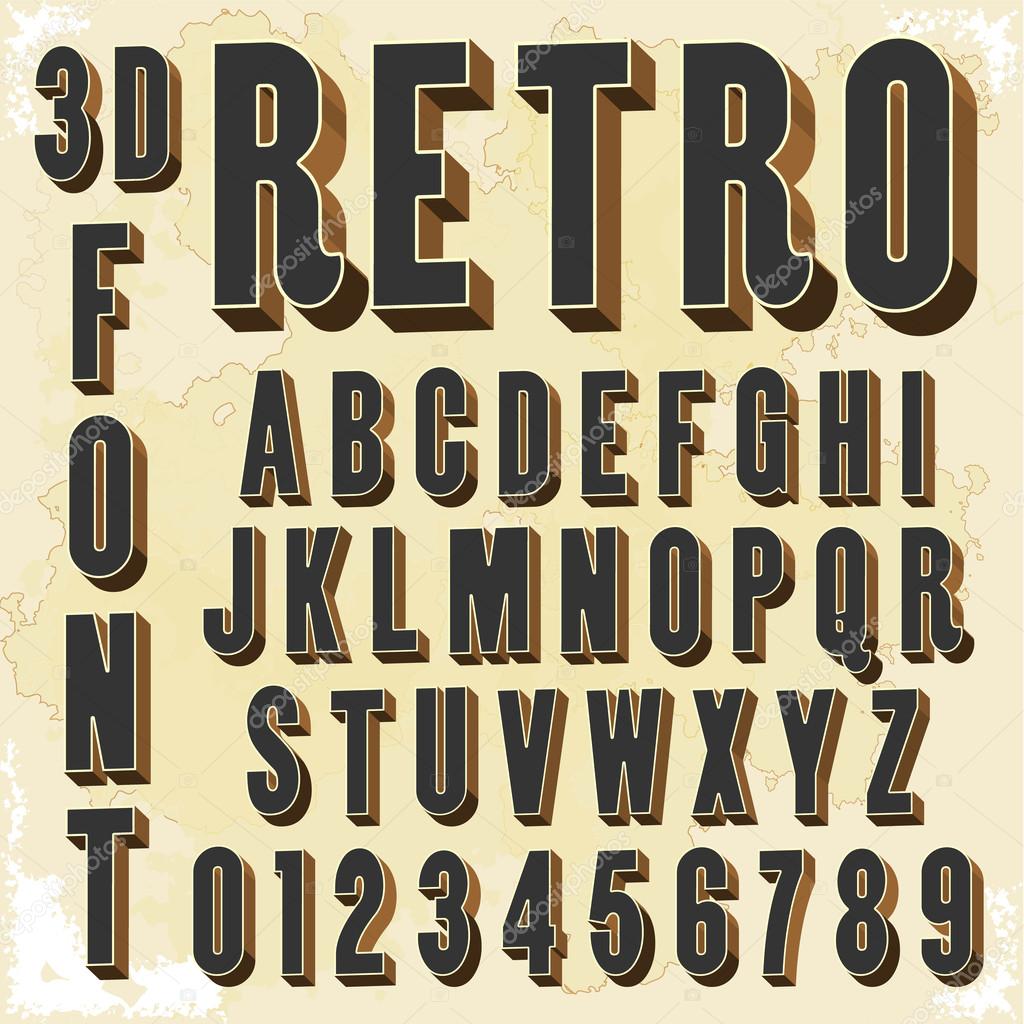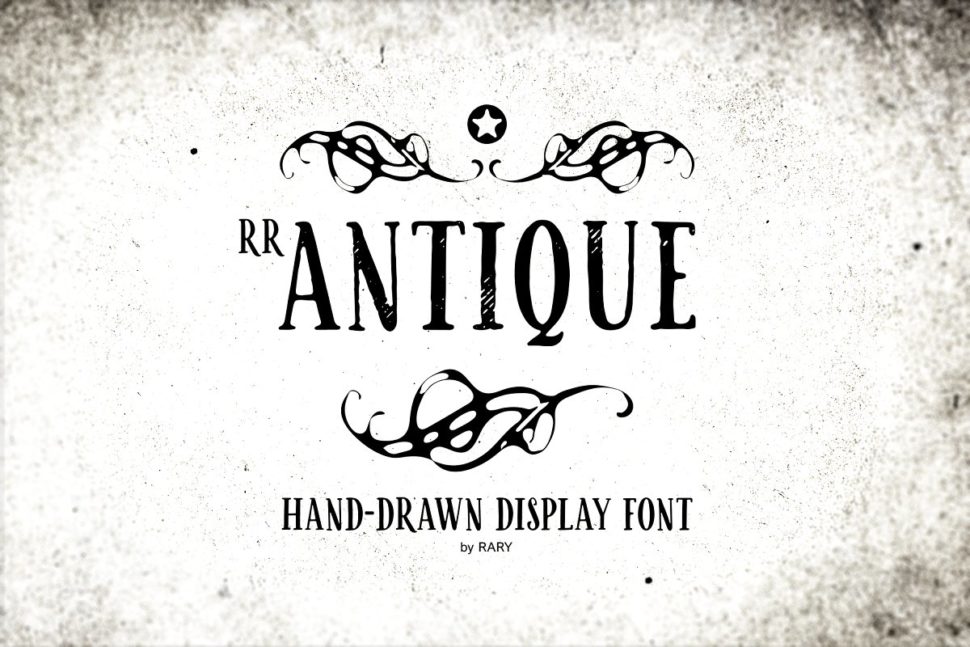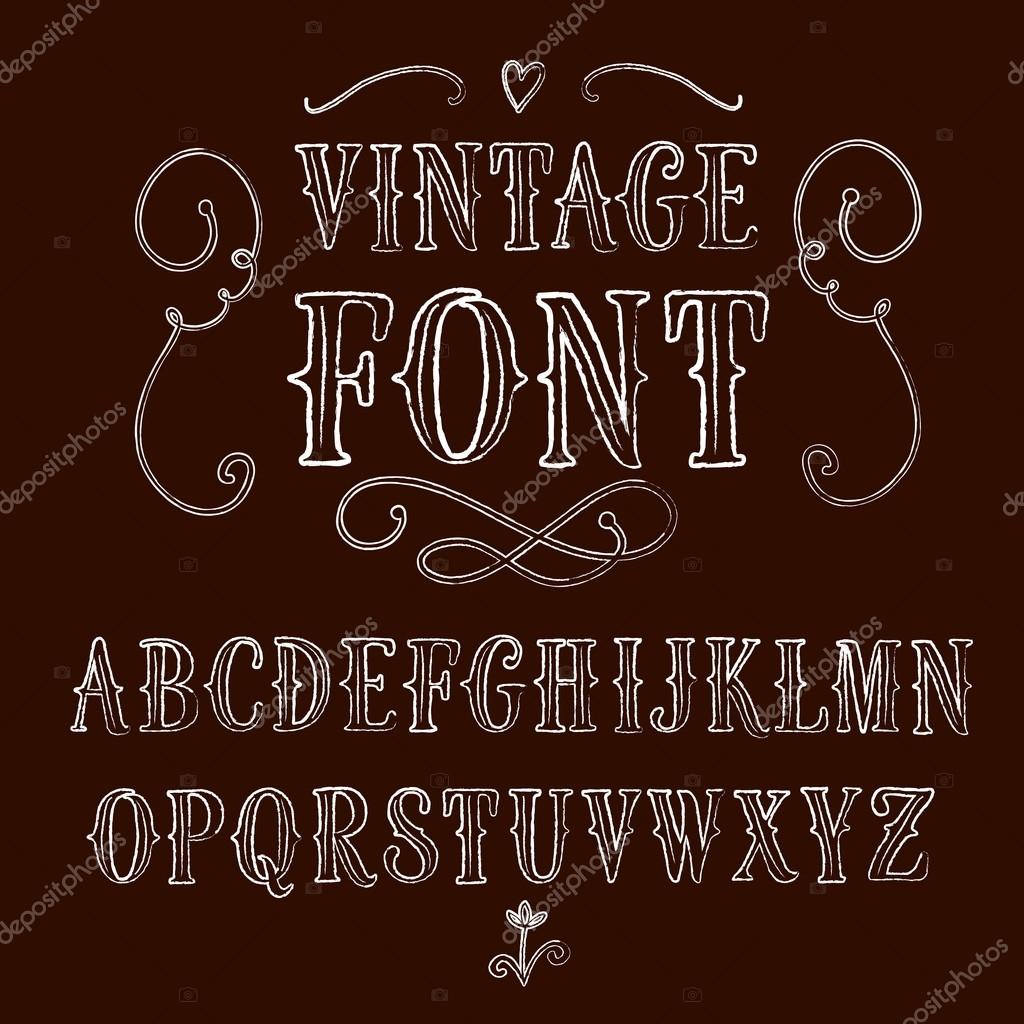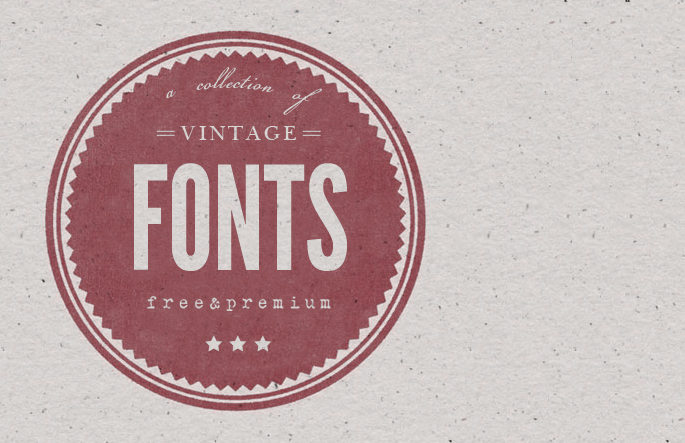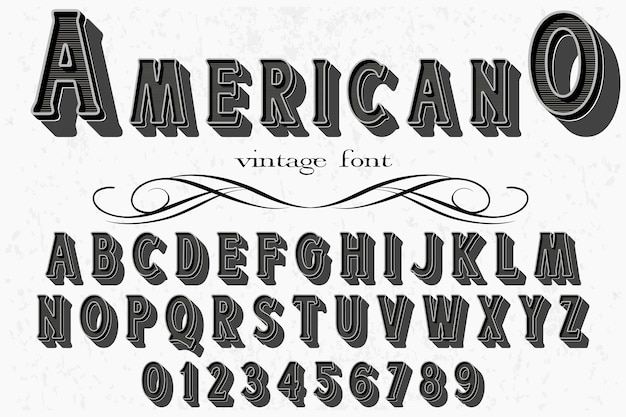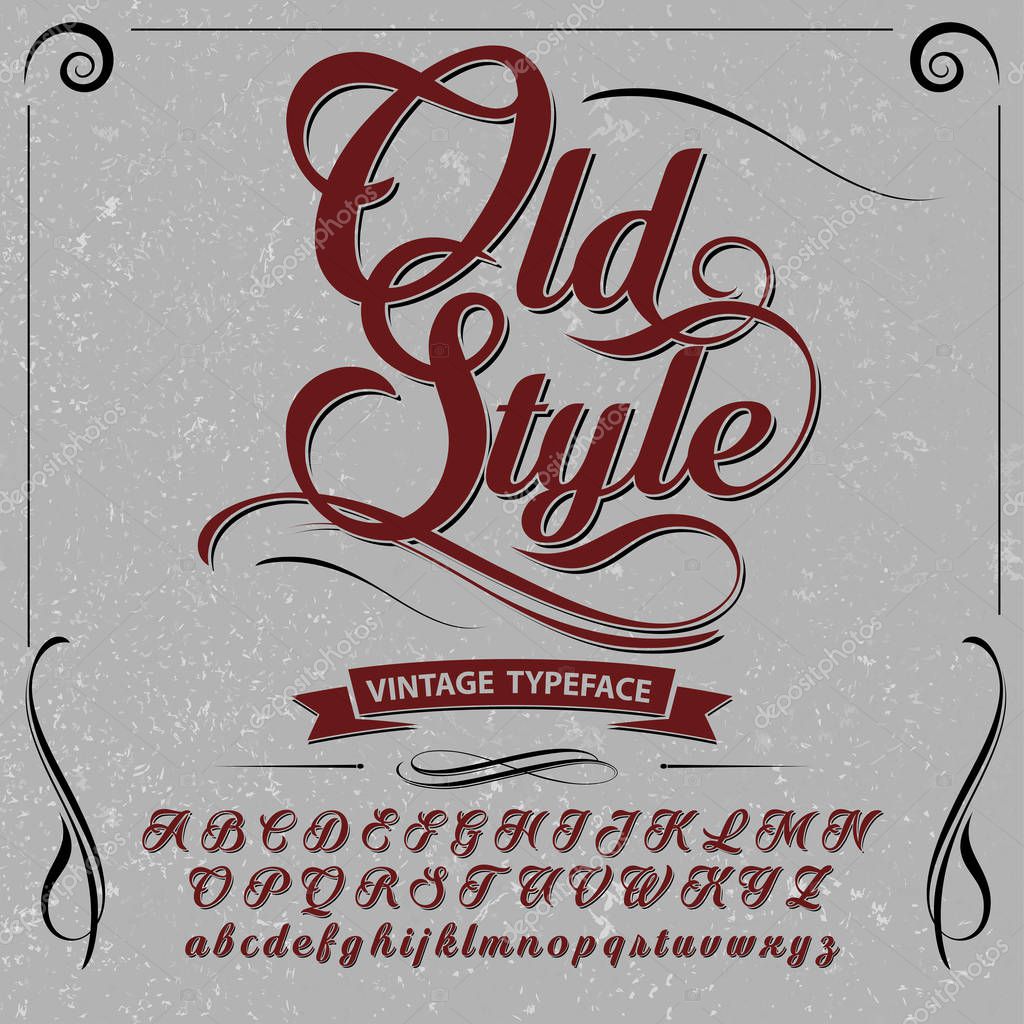
Взгляните на эти замечательные старинные шрифты. Они могут быть не новыми, но они все равно могут принести вам такое влияние, которого вы никогда не видели.
Есть одна веская причина, по которой старинные шрифты все еще используются сегодня. Они выдержали испытание временем и доказали, что могут продолжать добавлять уникальную привлекательность к дизайну, несмотря на то, что на рынке появляются более современные тенденции.
1. Caja
2. Cassannet Plus Regular
3. Bough Handdrawn Typeface
4. Bernier Type Family
5. Nickainley Monoline Script Font
6. Duwhoers Modern Brush Font
8. Refuge Handcrafted Font
9. Blnc Round
10. Draft Display
11. Kino 40 Typeface
12. Hobric Rough
13. Contact High
14. Ren free font
15. Arkana Script Vintage Font
16. Canyons Vintage Script
17. Rising Star Monoline Script
18. Zeyk Brush Typeface
19. Lauren Script Font
20. Awesawez Script
21. Diamor Script
22. Little Cutie
23. Sitka Brush
24. Logawa Script
25. Elrotex Brush Font
26. Something Wild Free Font
27. Arabella
28. Morracle Font
29.
Бесплатные винтажные и ретро шрифты
Дизайн в стиле ретро предназначен для отсылки в прошлое, и желательно, не меньше чем лет на 40-50. Такой дизайн передает особую атмосферу, придает проекту выдержанность хорошего коньяка и даже немного играет на нащей ностальгии. Для этого используют различные методы — например, элементы в винтажном стиле, ретро паттерны, текстуры, цветовые гаммы. Важное место здесь занимает типографика. Для свежей подборки мы нашли 17 самых атмосферных (и бесплатных!) ретро шрифтов, которые отражают настроение 1920—1960 годов прошлого века.
Matchbook
Bazar, Medium
Embossed Black
Ugly Qua
Hill House
Shrewsbury-Condensed Bold
Caslon
Seaside Resort
Fontleroy Brown
Fusty Saddle
Dirty Ames
Just Old Fashion
Goudy Bookletter 1911
Circus Ornate
BP Script
Rocket Script
Anagram
Copper
Названия фильмов 80-х и начала 90-х годов вдохновляют дизайн шрифта Copper от Drizy. Его острый стиль шрифта с заостренными штрихами и острыми углами особенно хорошо подходит для логотипов групп, плакатов мероприятий и приглашений. Шрифт доступен в форматах TTF и OTF .
The Moonlight